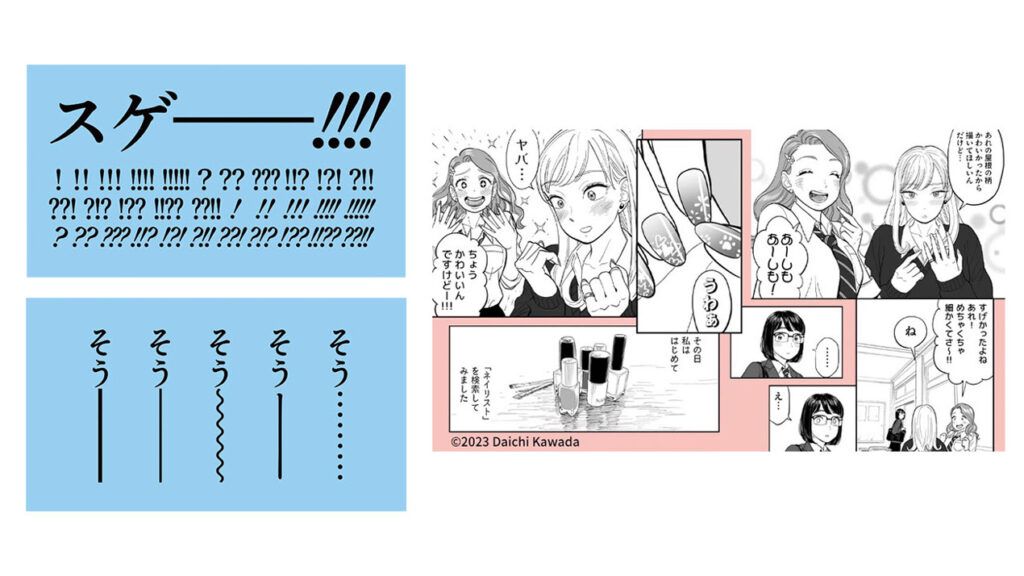
アドビ セルシスの「CLIP STUDIO PAINT」がAdobe Fontsの新仕様 Adobe-Manga1-0に対応へ
アドビ株式会社は、株式会社セルシスが提供しているイラスト・マンガ・Webtoon・アニメーション制作アプリ「CLIP STUDIO PAINT」が、「Adobe-Manga1-0」に対応する予定であることを発表した。
これにより、マンガのセリフ表現に特化した特殊文字の互換性が向上し、より豊かなマンガ表現が行えるようになる。
アドビの新しいテキストフォーマットが業界標準として今後活用されていくと、様々なマンガフォント間の互換性と、相互運用性が向上することが期待される。セルシスの「CLIP STUDIO PAINT」は、マンガを制作する多くのクリエイターが利用しており、アドビの「貂明朝アンチック」をはじめとしたマンガ向けのフォントの活用が想定される。このことから、セルシスとアドビは、フォントの互換性を高めるための情報交換を行っている。
なおアドビは、2023年11月、マンガに最適なフォント「貂明朝アンチック」と合わせて、業界標準を目指して新しく定めた文字コレクション「Adobe-Manga1-0」を発表している。